汉字是中华民族的一种精神的象征,从仓颉造字到现在中国汉字有着特殊的含义,同时也具有着不同的形态的美感。从古代到现代,汉字字体不断的演化,而书写的方式也在不断的发生变化,到现在为止汉字字体非常丰富。那么想要下载汉字字体下载大全,在哪里可以下载呢?
汉字字体,无论是从其含义和其他的字体形态来说,都包含着丰富的意义。不仅给人传情达意,而且能够给人以美感。尤其是在艺术设计方面使用不同的字体,表达情感与美感。作为汉字字体大全的平台,字体视界拥有很多类型的字体。包括经典的字体,比如,楷体、黑体、宋体、圆体、隶书。还包括着个性化的字体,每一款字体都注入了设计者的精心设计,也体现了中华文化的博大精深。
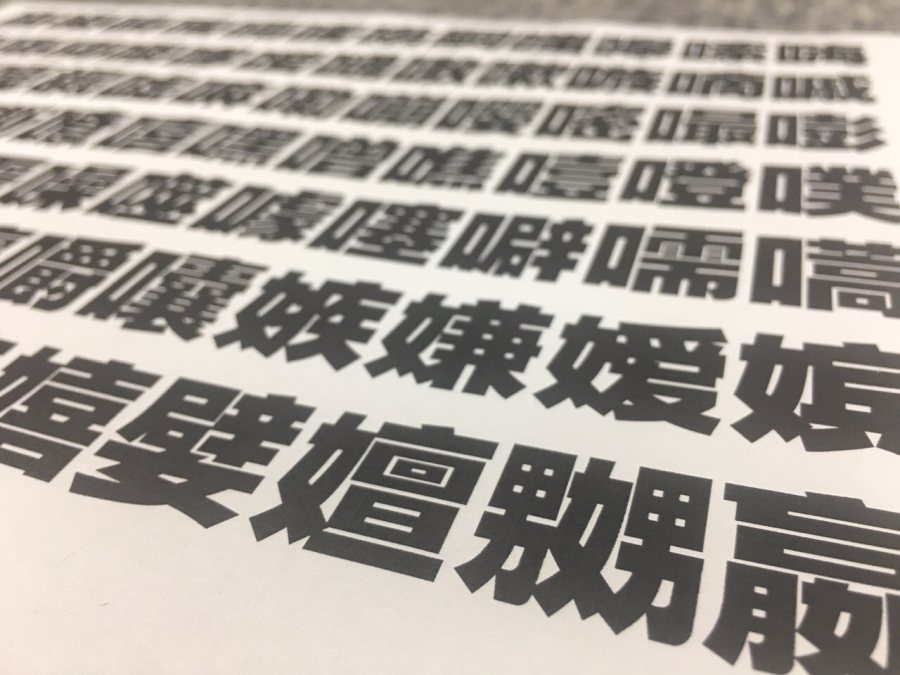
在现代多元化的社会当中,人们对个性化的追求是越来越明显,那在彻底方面人们对他的要求也越来越大。一个字代表了一个人,一个字体代表了这个人的个性,代表了他为人处事的一种精神代表了他自己的人物的性格特征。所以在个人使用自己的时候,也有特殊的癖好,有些设计师经常使用自己的御用字体,因为喜欢。那么想要进行汉字字体大全下载,可以登录字体视界平台。它不仅包含了传统的经典的字体还具备了时下比较流行个性化的字体大全,满足了年轻人设计师的一些需求,让整个设计行业能够多元化,获得更多的美感。